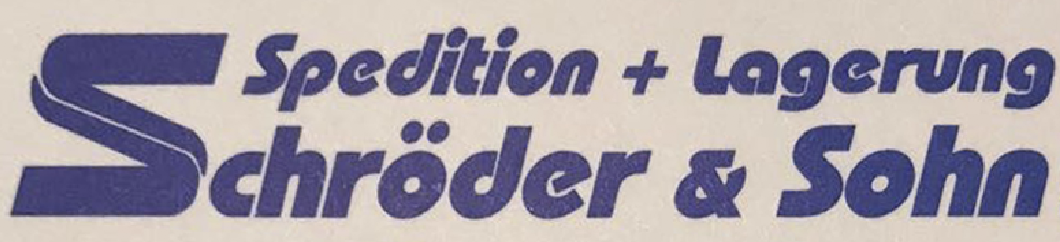
Suche Schriftart von Spedition
ich bin auf der Suche nach der Schrift vom Logo aus dem Anhang. Habe die Schriftart schon öfters mal in der Zeitung bei Anzeigen gesehen, nur leider habe ich nichts gefunden, auch nicht über whatthefont. Digital habe ich auch nichts vorliegen, nur ein Foto von einer ganz alten Visitenkarte.
Weiß von euch jemand, wie sich diese Schriftart nennt? Das "S" von Schröder habe ich schon nachgebaut, es geht um die anderen Wörter.
Die kursive Version gibt es im Originalschnitt nicht, man kann sie aber in diversen Freefonts zweifelhafter Qualität finden.